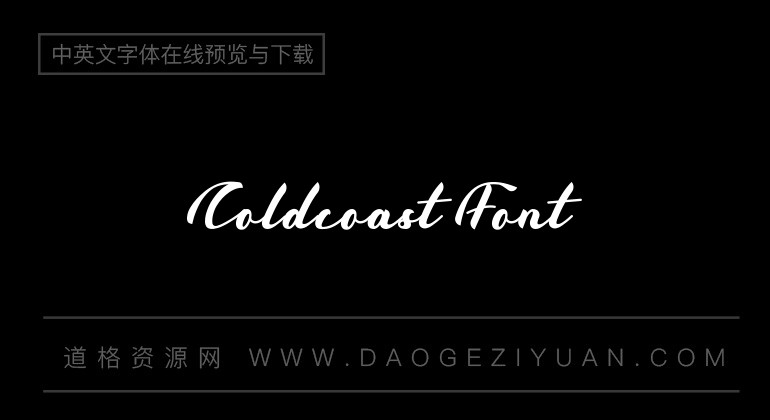
Coldcoast Font
Coldcoast Font是一种现代艺术风格的字体,具有独特的外观和风格。它的设计师是来自日本的Yasir Ekinci,这个字体的特点是线条简洁明了、形态流畅,具有一定的科技感和未来感。Coldcoast Font 适合用于设计海报、标志、标题、宣传册、包装等等。 Coldcoast Font 提供了多种字重和变体,包括正常、粗体、斜体、斜粗体等,可以满足不同设计需求。该字体还提供了支持多种语言的字符集,包括英文、西班牙文、葡萄牙文、德文、法文、意大利文等,方便跨国设计和多语言排版。 总而言之,Coldcoast Font是一款极具现代感和艺术气息的字体,适合各种设计场景。
Coldcoast Font是一款非常不错的手写艺术字体,具有很好的视觉感,适合于文化类的宣传设计、商业类品牌的广告和产品包装设计以及个性化文字排版等较多场景。